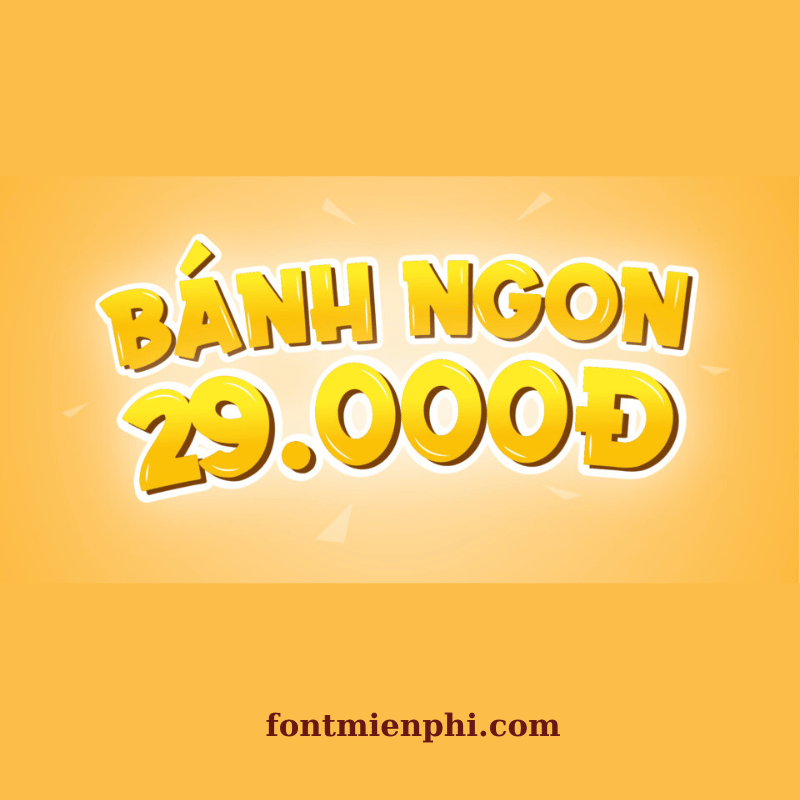
Font Việt hóa 1FTV VIP Bakari
Font Việt Hóa 1FTV VIP Bakari – Phong Cách Thiết Kế Độc Đáo
Font Việt hóa 1FTV VIP Bakari là bộ font chữ cao cấp, được thiết kế dành riêng cho người dùng Việt Nam. Với kiểu dáng hiện đại, nét chữ mềm mại nhưng không kém phần cá tính, Bakari phù hợp cho nhiều dự án thiết kế, từ in ấn, quảng cáo đến nghệ thuật sáng tạo.
• Hỗ trợ đầy đủ Tiếng Việt: Bao gồm các ký tự có dấu, đảm bảo tính thẩm mỹ và dễ đọc.
• Đa dạng phong cách: Phù hợp với poster, logo, bìa sách, và các ấn phẩm truyền thông.
• Chất lượng cao: Đường nét sắc sảo, không bị vỡ hình khi phóng to.
1FTV VIP Bakari là lựa chọn hoàn hảo cho designer muốn tạo điểm nhấn trong tác phẩm của mình. Font chữ này đặc biệt phù hợp với các dự án thời trang, âm nhạc, và quảng cáo sáng tạo.